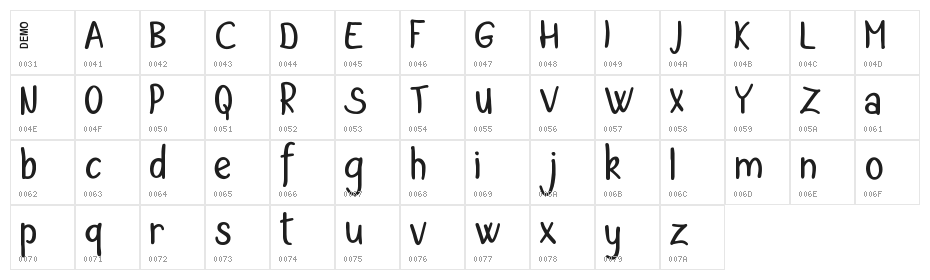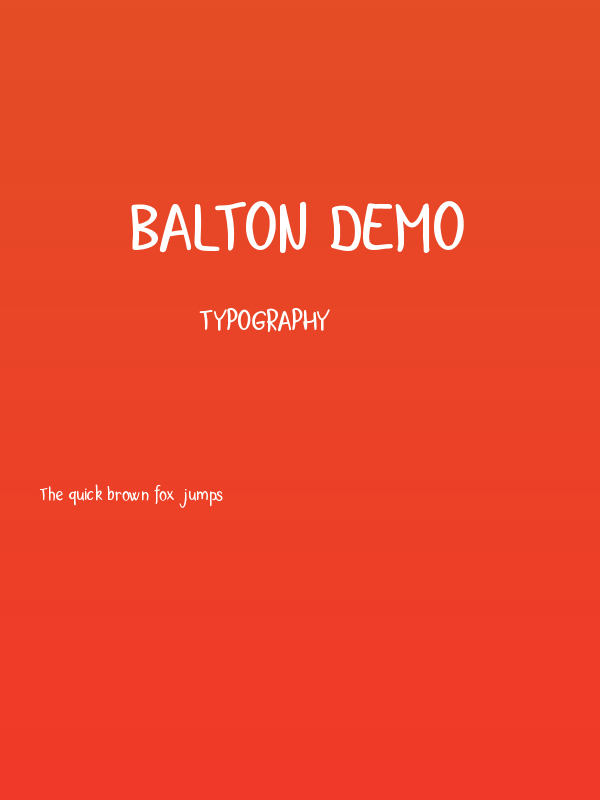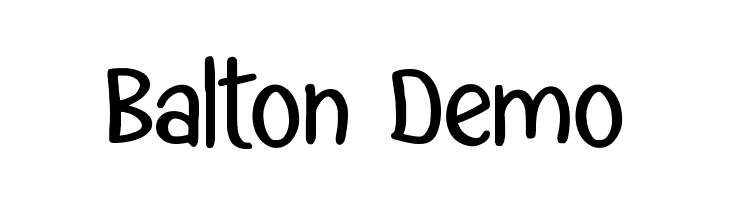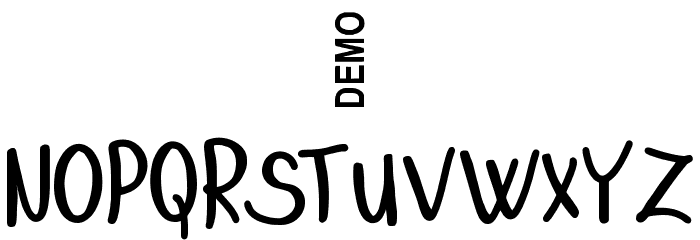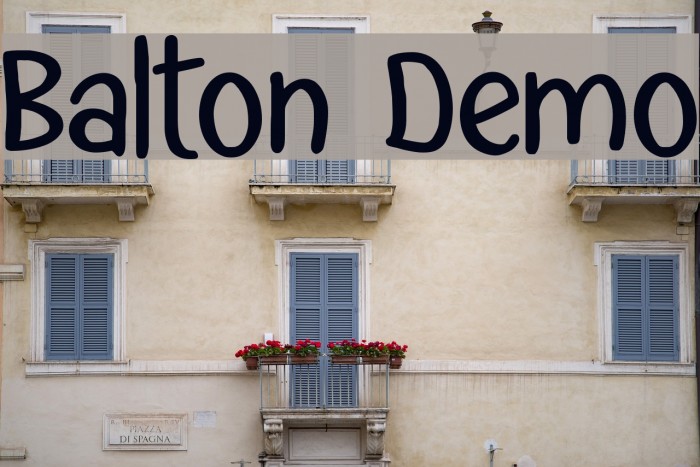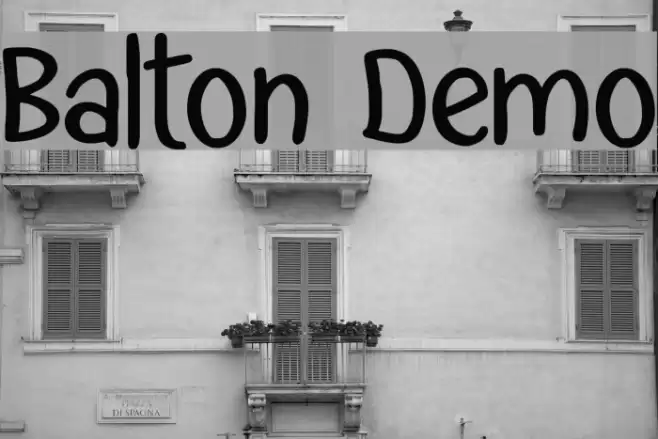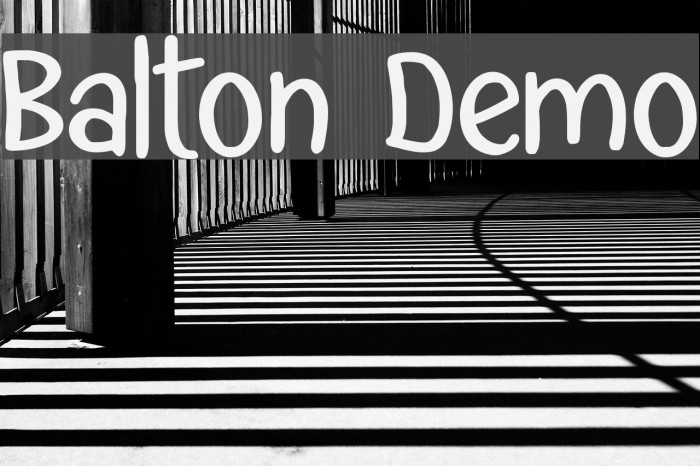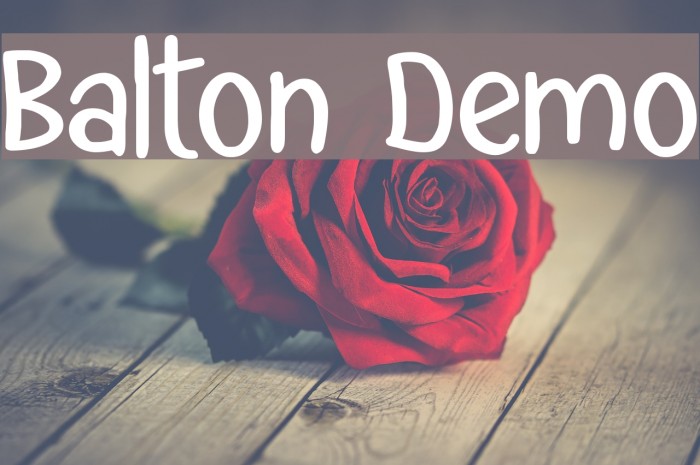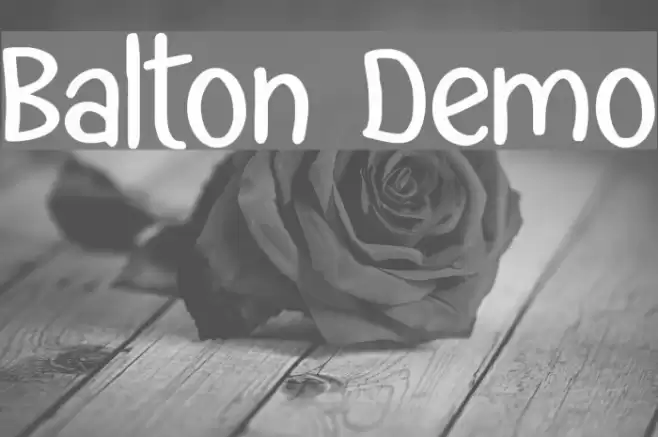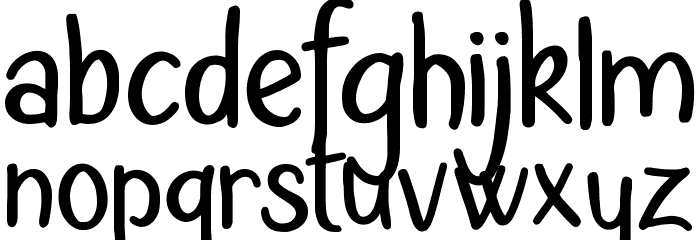
Balton Demo Font
| Estilo geral | Casual, Playful |
| Caso de uso | Headlines, Logos, Informal Text |
| Projetos propostos | Ideal for children's books, playful branding, greeting cards, and informal invitations. |